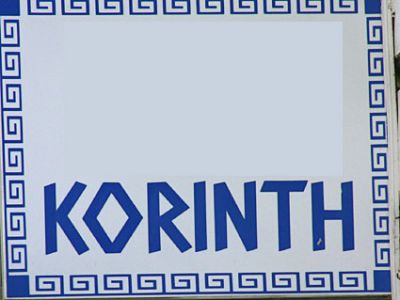
Welche Schriftart ist das, oder ist sie selbst gestaltet?
Hallo, wäre dankbar für die Auskunft dieser Schriftart. Gibt es die überhaupt, oder ist sie selbst gestaltet oder umgestaltet worden? :roll:1416_korinth_1.jpg
MyFonts gibt keine vernünftigen Resultate, auch nicht mit diesem Ausschnitt:
Relativ nah dran sind die Caesar Brute BTN oder als Klassiker, die Lithos Black, aber das sind sie eben beide nicht genau. Diese Schrift sieht fast aus, wie mit dem Edding entworfen, scheint mir etwas gestaucht zu sein, ich mag mich aber auch täuschen.